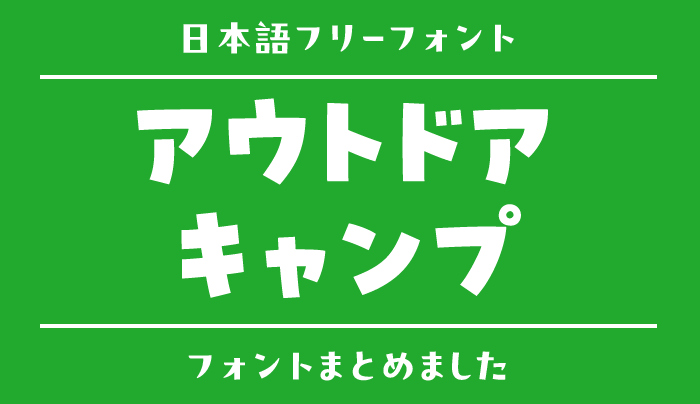
「アウトドア・キャンプ」にぴったりな日本語フリーフォント
「アウトドア・キャンプ」にぴったりな日本語フリーフォント15選
キャンプの記録、アウトドアイベントの告知、道具の紹介。自然を扱うデザインでも、無骨なギアを見せたいのか、家族で過ごす穏やかな時間を伝えたいのかで、合う日本語フォントは変わります。
今回はフォントラボから、アウトドア・キャンプに使いたい日本語フリーフォントを15個選びました。雰囲気を作る見出し用と、持ち物や施設案内を読むためのフォントを分けて紹介します。安全に関わる注意事項は装飾性よりも読み取りやすさを優先しましょう。
アウトドアの過ごし方に合わせて選ぶ日本語フリーフォント
焚火フォント
おすすめの場面キャンプ動画の表題/焚き火の写真/夜のイベント告知
炎を思わせるフォントで、火を囲む時間に。
「焚火フォント」は、炎の揺れを思わせる変形や線のつながりが、夜のキャンプ写真に合うフォントです。焚き火を囲む動画のタイトルなど、短い言葉を主役にする使い方におすすめ。太さを変えると印象も変わるので、写真の明るさに合わせて試せます。火の扱いなどの注意事項は、この装飾フォントではなく素直なゴシックで明確に伝えましょう。
ボトムズG
おすすめの場面キャンプギア紹介/無骨な表紙/アウトドア企画名
かすれたフォントで、道具を使い込んだ表情を。
「ボトムズG」は、輪郭のかすれが、使い込まれた道具や古い印刷物を連想させるフォントです。金属や帆布などの質感が見えるギア写真と合わせると、無骨な雰囲気が出せます。商品仕様を読むためのフォントではなく、企画名や短い見出しにおすすめ。小さくすると欠けが目立ちやすいため、完成サイズで判読できるか確認しましょう。
源直ゴシック
おすすめの場面道具レビューの表題/設営ガイドの見出し/イベント名
直線的なフォントで、機能的な道具の印象に。
「源直ゴシック」は、角張った直線が特徴のゴシックフォントです。テントや収納用品など、構造や機能を見せる企画の見出しに向いています。柔らかな自然写真に硬質な文字を合わせることで、アウトドアギアの存在感も引き出せます。寸法や仕様は標準的なフォントで整理し、タイトルの個性と数値の読みやすさを使い分けましょう。
Oradano明朝
おすすめの場面キャンプ日誌/旅のしおり/古道具を扱う特集
活字のかすれで、残しておきたい記録に。
「Oradano明朝」は、昔の活字印刷を思わせる不均一な線が魅力の明朝フォントです。キャンプ日誌や古い道具の特集に使うと、時間を重ねたような雰囲気になります。整いすぎたフォントよりも、記録の手触りを出したい人におすすめ。地名や珍しい漢字が表示できるかを確認し、かすれが読みにくくならない大きさで使いましょう。
デラ・ムーア
おすすめの場面冒険感のある表題/野外イベント/キャンプ飯の見出し
切り紙のようなフォントで、野外の楽しさを。
「デラ・ムーア」は、先端の三角形の処理や切り紙のような形が特徴の太いフォントです。野外イベントやキャンプ飯など、少し冒険的でにぎやかな企画におすすめ。短いタイトルなら独特の輪郭がよく見え、写真の勢いにも負けません。地図や長い手順は別のフォントに任せ、目を引かせたい数文字に使うと個性を活かせます。
あるぺんフォント
おすすめの場面登山やキャンプの記録/写真へのコメント/手帳風の表紙
ペンの揺れがあるフォントで、現地の気分を。
「あるぺんフォント」は、筆圧やかすれが感じられる手書きフォントです。キャンプの写真に短い感想を添えたり、手帳風の表紙を作ったりすると、体験した人の声が伝わります。無料版の漢字は教育漢字が中心なので、山名や地名は実際に試し打ちを。フォントを使った商標登録はできないため、ブランド用途では配布条件にも注意してください。
きろ字
おすすめの場面フィールドノート/写真のキャプション/キャンプ日記
読みやすい手書きフォントで、観察を言葉に。
「きろ字」は、整った手書きの形が、記録を自然に見せるフォントです。天気や景色の感想、道具を使った印象など、少し長めのコメントにもおすすめ。強いタイトルフォントと違い、写真の脇で語りかけるような役割を担えます。手帳らしい雰囲気を作る場合も、文字を小さくしすぎず、行間をゆったり取って読みやすく整えましょう。
のんびりフォント
おすすめの場面休日キャンプの表題/休憩風景/親子の思い出
ゆるやかなフォントで、急がない時間を。
「のんびりフォント」は、細い筆の揺れが、力を抜いた休日に合う手書きフォントです。コーヒーを飲む時間やテントの中で休む場面など、穏やかな写真に一言添える使い方におすすめ。漢字は一部のみなので、長い文章をすべて組む前に確認しましょう。案内フォントと役割を分けると、必要な情報を保ちながら、のんびりした空気を加えられます。
源雲明朝
おすすめの場面自然を読む小冊子/キャンプエッセイ/景色の紹介
墨だまりのある明朝フォントで、静かな自然に。
「源雲明朝」は、線の交わりに墨だまりを感じる、やわらかな明朝フォントです。森や湖の写真を使う冊子や、キャンプ体験を文章で読ませる記事におすすめ。太いアウトドア系フォントとは異なり、風景の静けさを中心にできます。写真に直接重ねる場合は線が背景に埋もれないようにし、余白へ配置する方法も試してみましょう。
いろは角クラシック
おすすめの場面自然観察のしおり/キャンプ場の紹介/読み物の見出し
古風なかなのフォントで、落ち着いた案内に。
「いろは角クラシック」は、ゴシックの形に古風なかなの線の運びを合わせたフォントです。自然観察の小冊子やキャンプ場の紹介で、素朴さときちんと感を両立したいときに向いています。かすれた装飾フォントほど荒々しくないため、情報のある見出しにも使いやすい候補です。写真の色数を抑えた紙面に合わせると、かなの表情がよく伝わります。
モボ
おすすめの場面キャンプギアの特集/イベント案内/チェックリストの見出し
ほどよい丸みのフォントで、現代的なアウトドアに。
「モボ」は、すっきりした形と丸みを合わせ持つゴシックフォントです。機能的なギア紹介を硬くしすぎずにまとめたいときや、若い世代向けのイベント案内におすすめ。見出しと補足の太さを変えると、少ないフォント数でページを整理できます。レトロな装飾に寄せすぎず、写真を主役にした軽快なレイアウトで試してみましょう。
源泉丸ゴシック
おすすめの場面ファミリーキャンプの案内/施設紹介/持ち物リスト
丸いフォントで、はじめての参加をやさしく案内。
「源泉丸ゴシック」は、整ったゴシックに丸みを加えたフォントです。ファミリーキャンプや初心者向けイベントで、持ち物や設備を読みやすく伝えたいときにおすすめ。見出しを装飾フォントにしても、案内部分を揃えると全体が落ち着きます。注意事項まで薄い色にせず、背景との明暗差と文字サイズを確保して使いましょう。
Rounded M+
おすすめの場面親子イベント/キャンプ場マップ/体験メニュー